王羲之草书《飞白帖》, 又名“飞白不能帖”,3行,19字。入刻《淳化阁帖》、《大观帖》、《澄清堂帖》、《绛帖》、《星风楼》、《宝贤堂》。
“飞白”是汉字书体的一种,以笔画中露白而得名。通常,对於笔画中的露白,人们称之为“渴笔”或“枯笔”。但飞白书中每一笔画都见渴笔。唐张怀瓘《书断》(上)载:汉灵帝诏蔡邕作《圣皇篇》,篇成,诣鸿都门,时方修饰鸿都门,见役人以垩帚成字,心有悦焉,归而为飞白之书。王隐、王倍并云:飞白变楷制也。本是宫殿题署,势既径丈,字宜轻微不满,名为飞白。故古有蔡邕创飞白书之说。
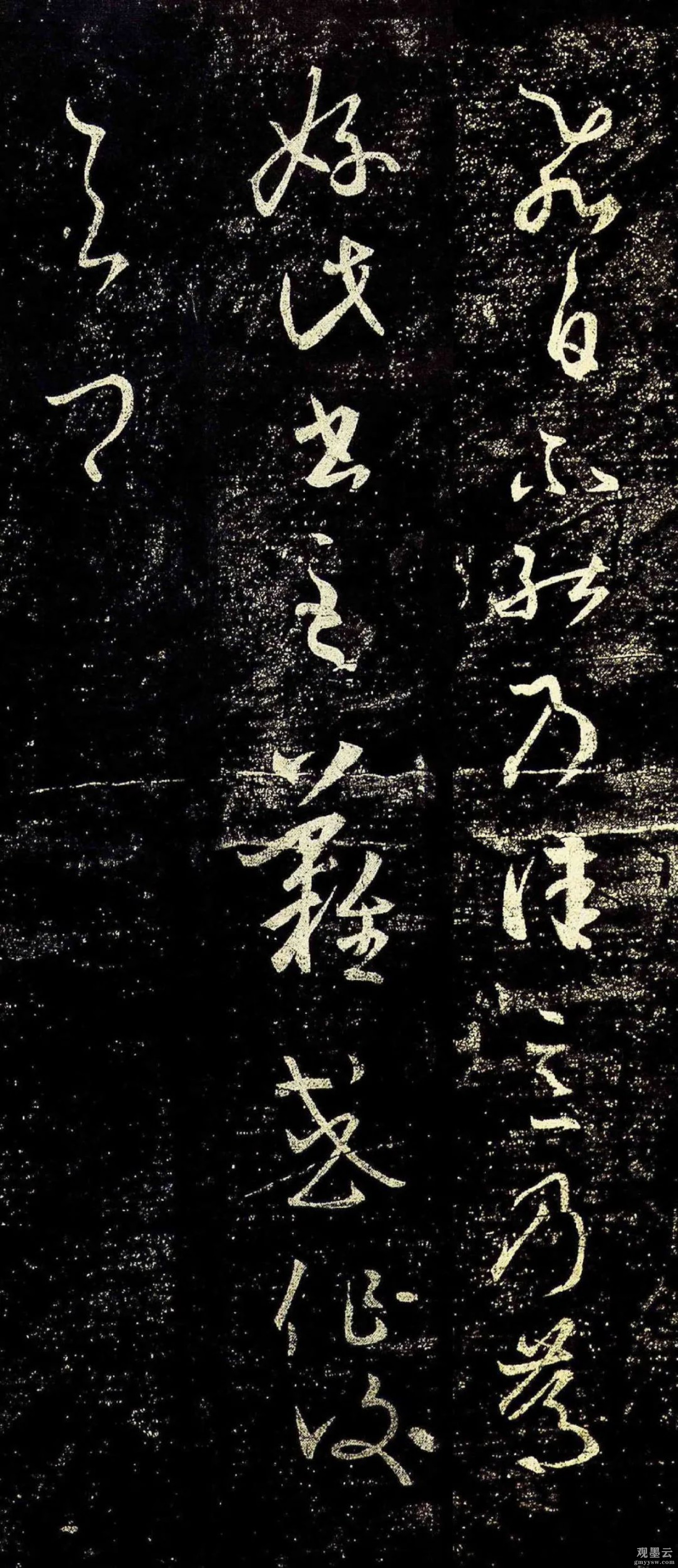
安思远藏本
释文:飛白不能乃佳,意乃篤好,此書至難,或作復與卿。